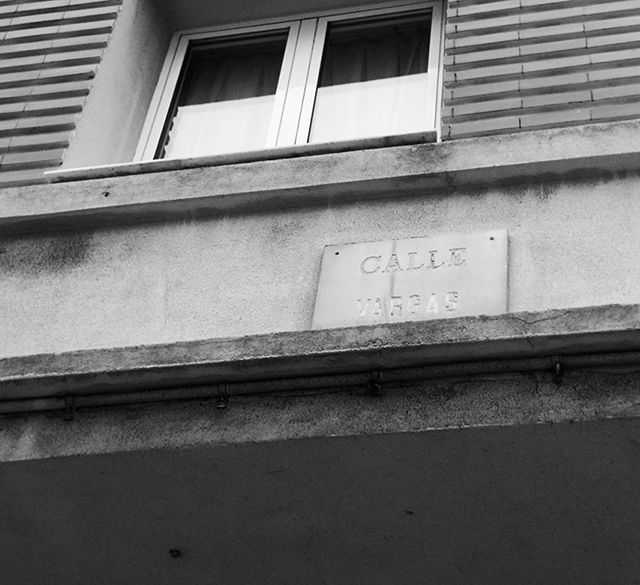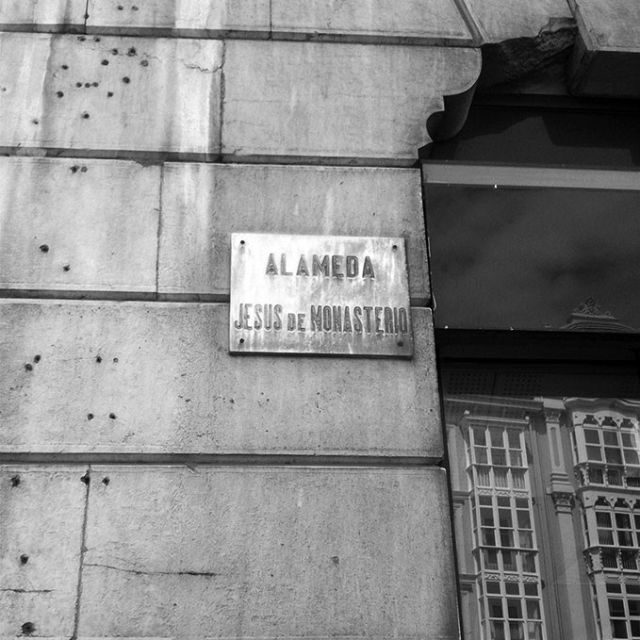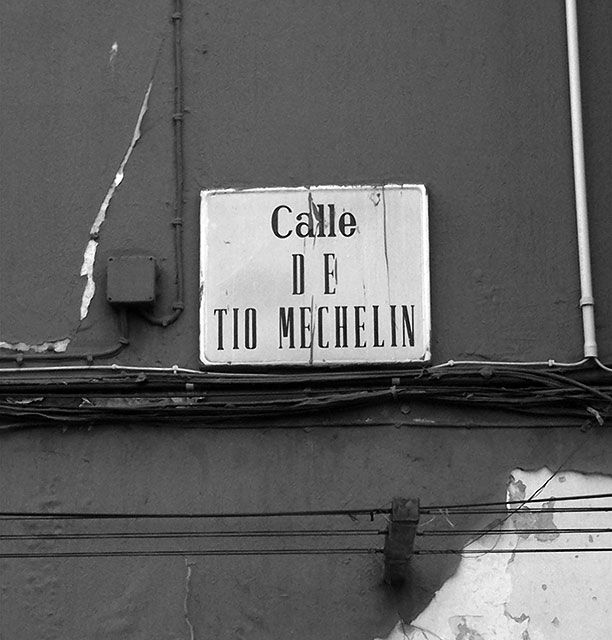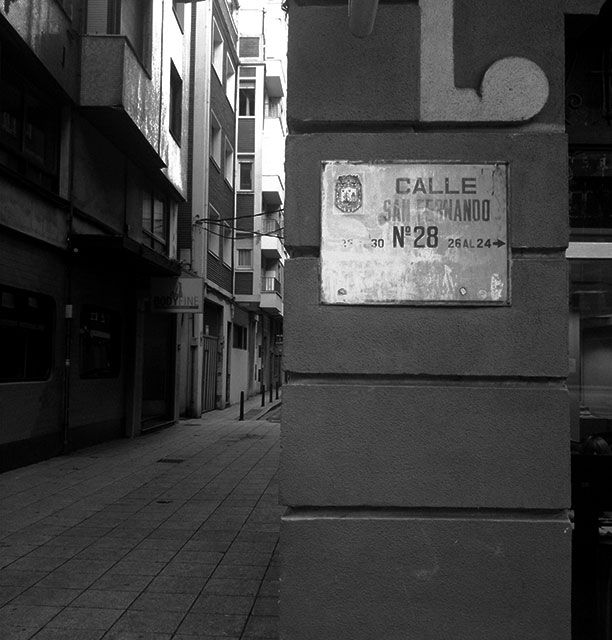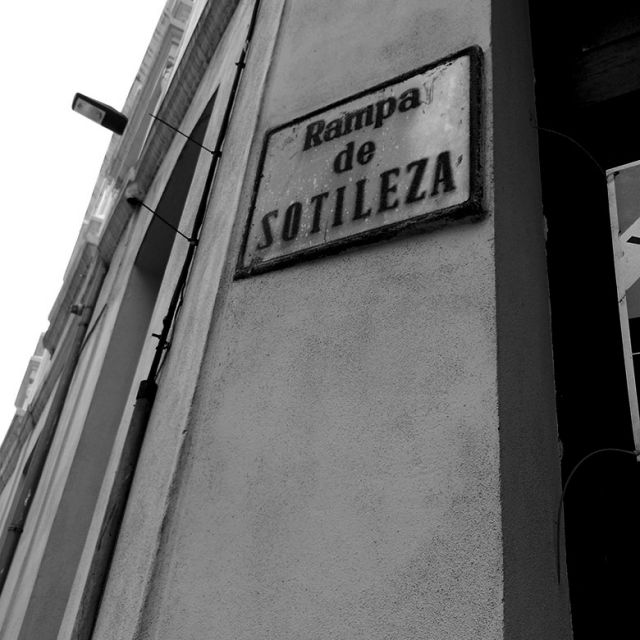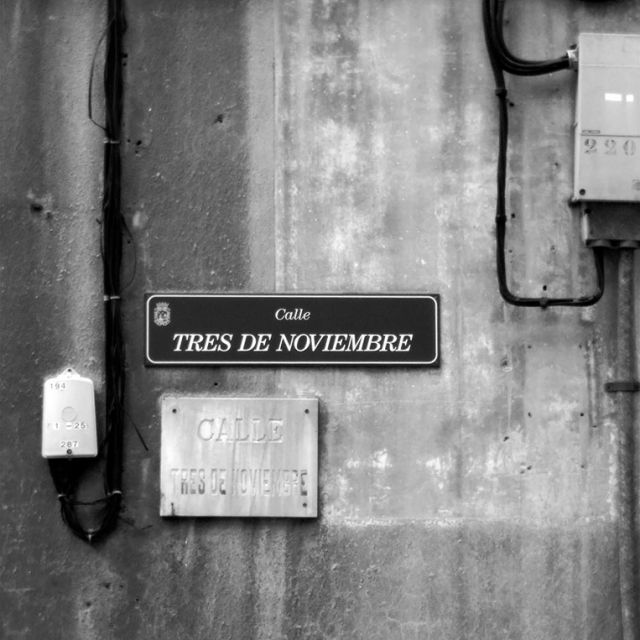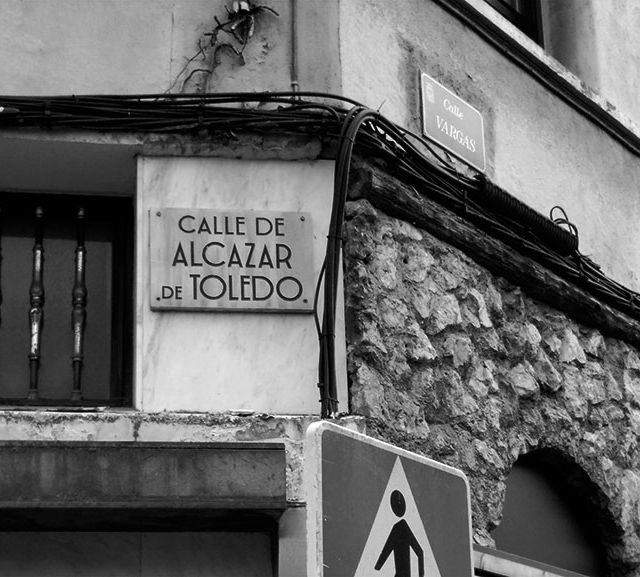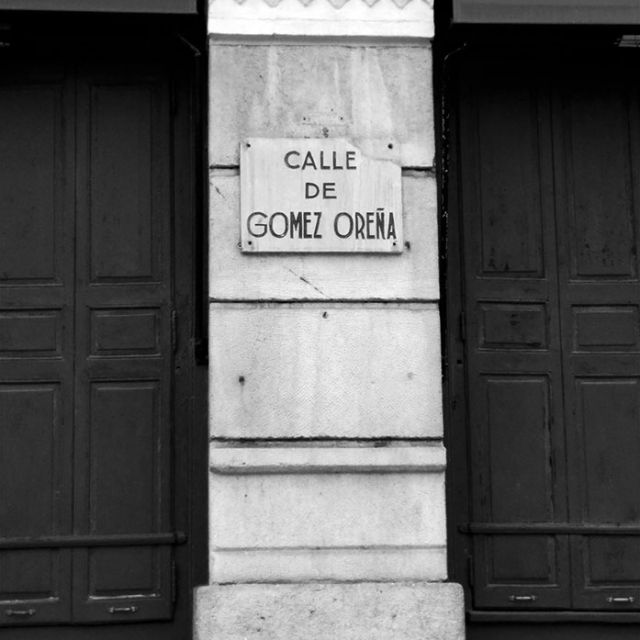
Placas de calle de Santander (I)
Hoy en día, gracias a los móviles y las aplicaciones de mapas, no nos hace falta (o casi) ir mirando en los edificios para saber en calle estamos. En Santander aún podemos encontrar diversas placas de tipología, materiales así como tipografías totalmente diversas que se fueron instalando en la ciudad.